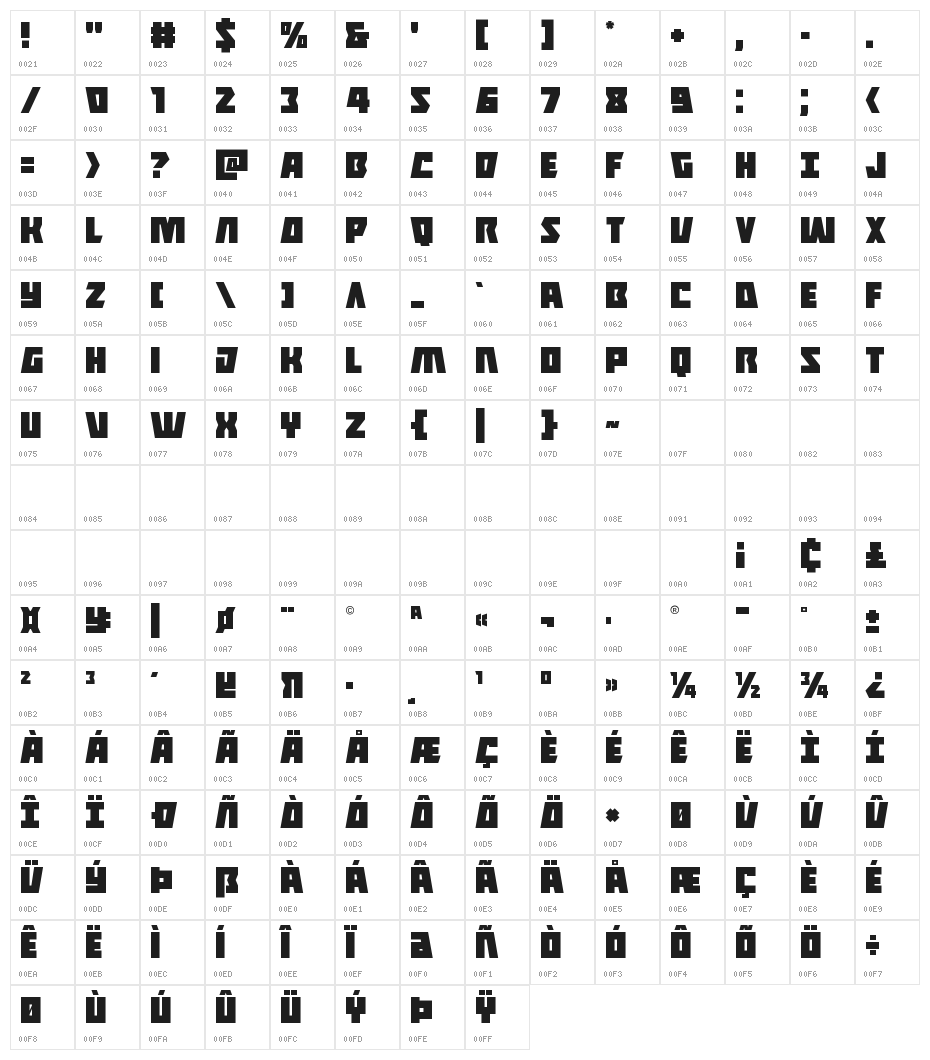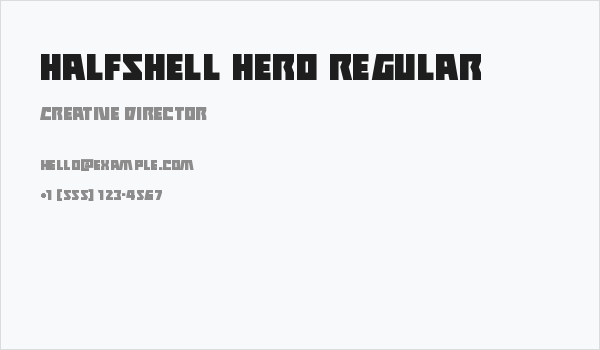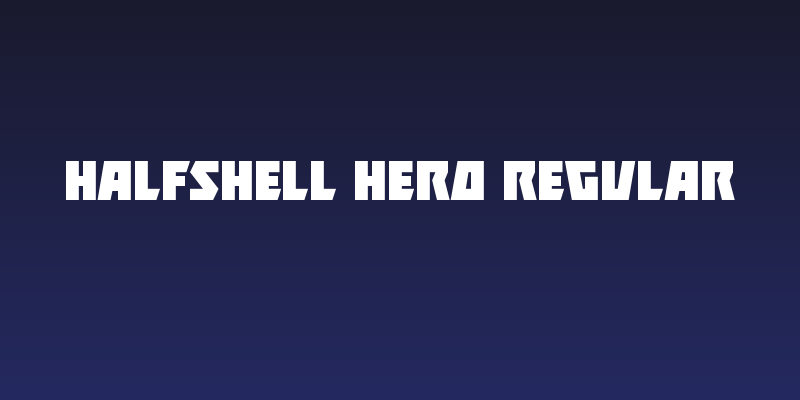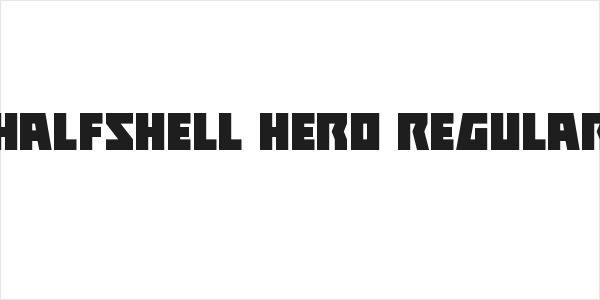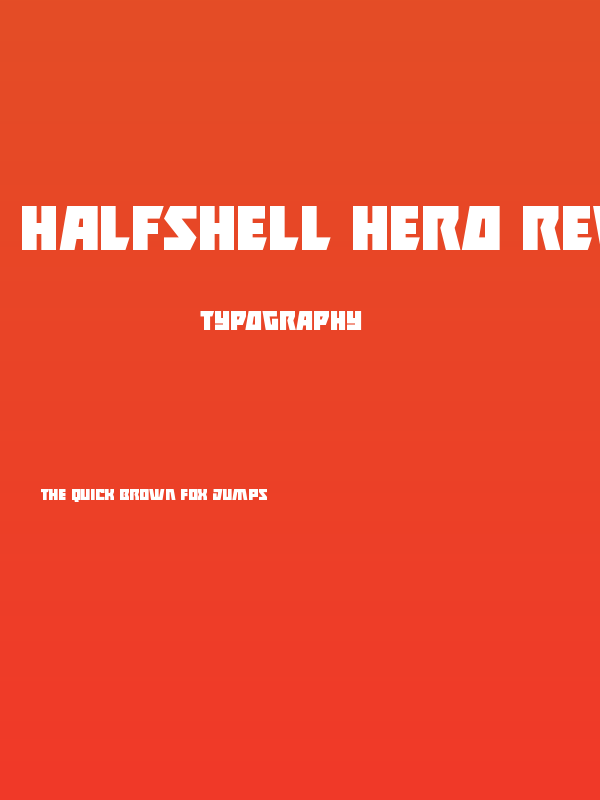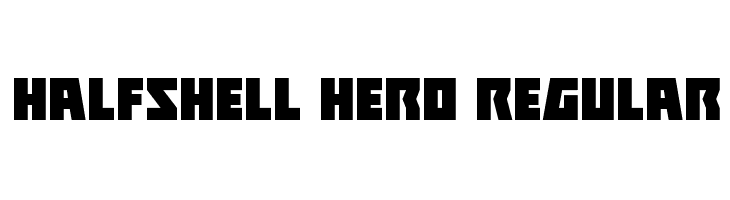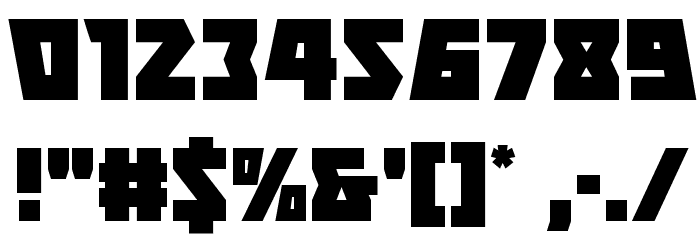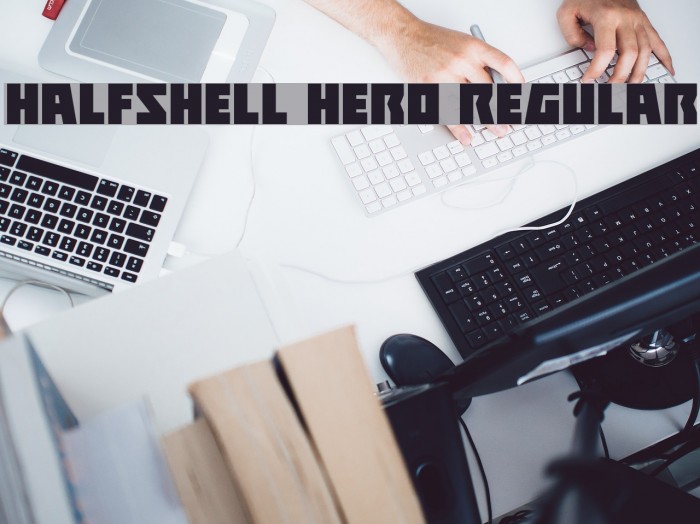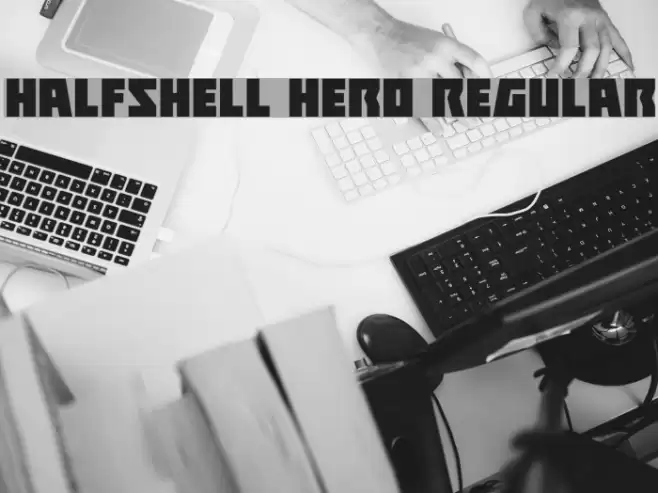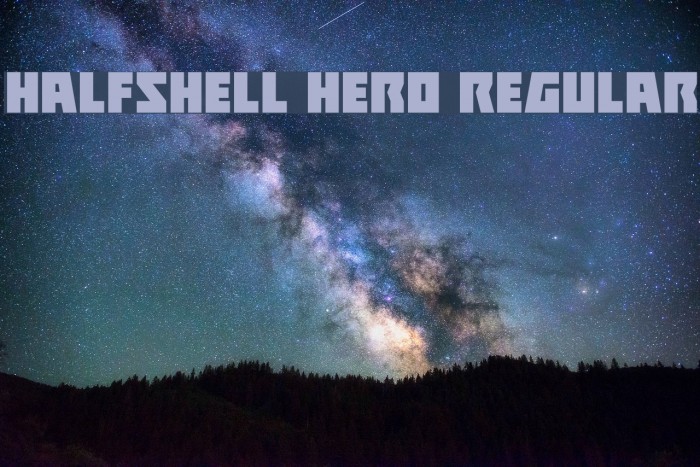
Halfshell Hero Regular Font
✎ Futuristic
| Vorgeschlagene Projekte | Ideal for video game titles, movie posters, branding for tech companies, and any project needing a bold, futuristic look. |